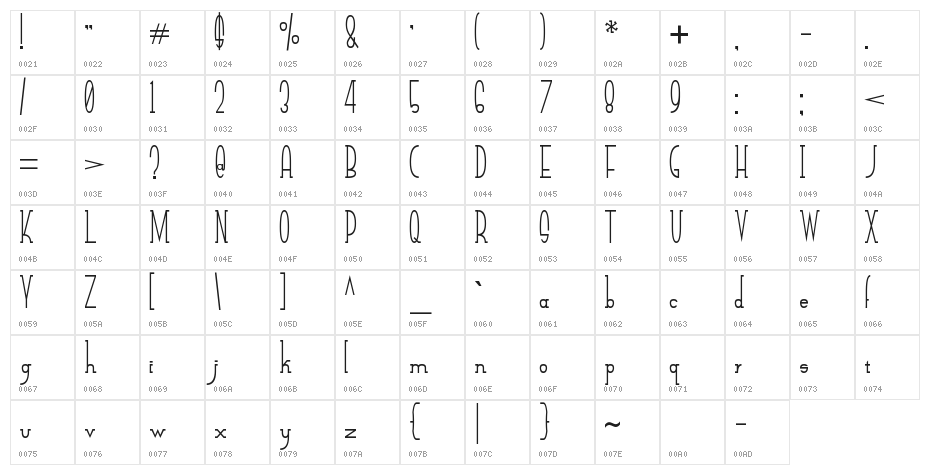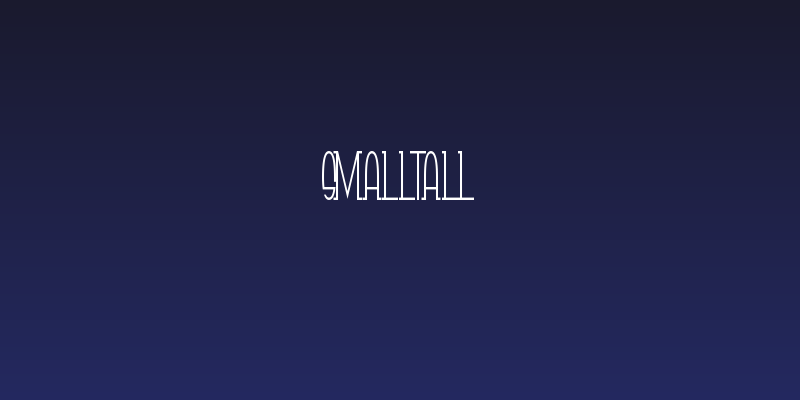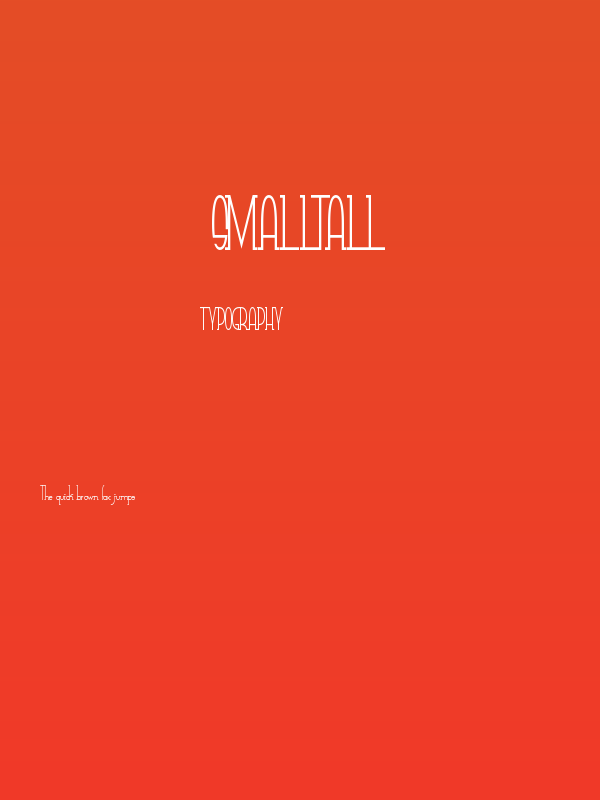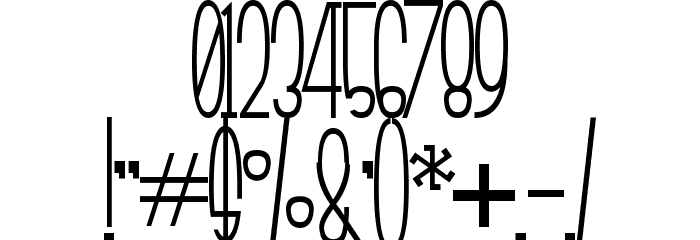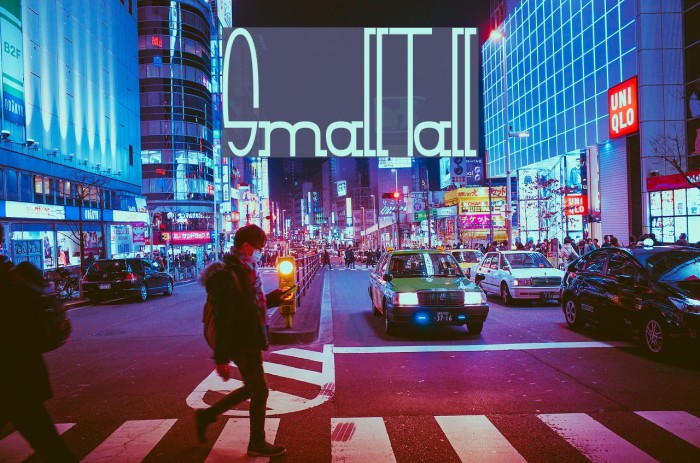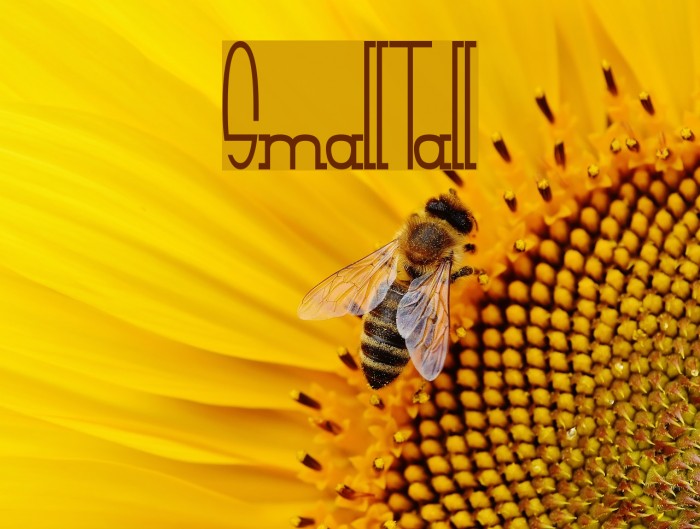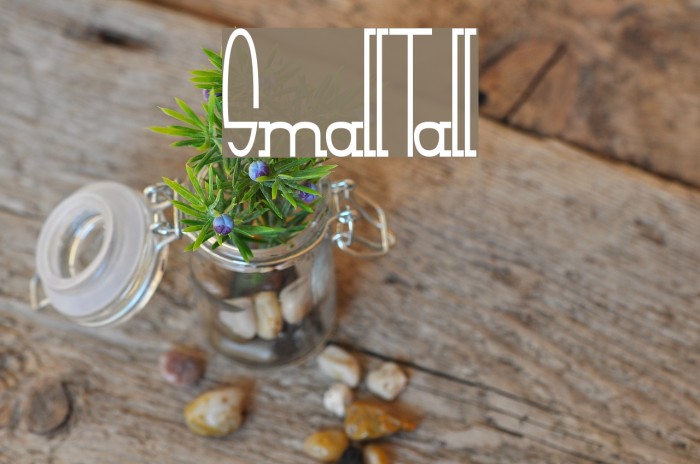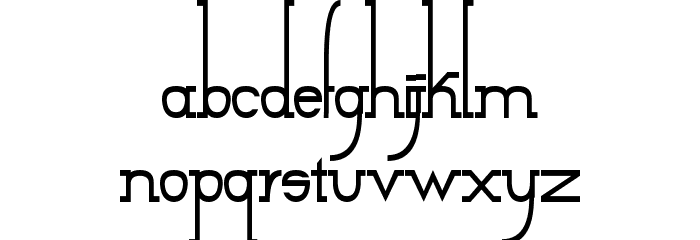
SmallTall Font
✎ Capitals
| Proyectos propuestos | Ideal for modern posters, fashion magazines, and branding projects that require a bold and elegant statement. |